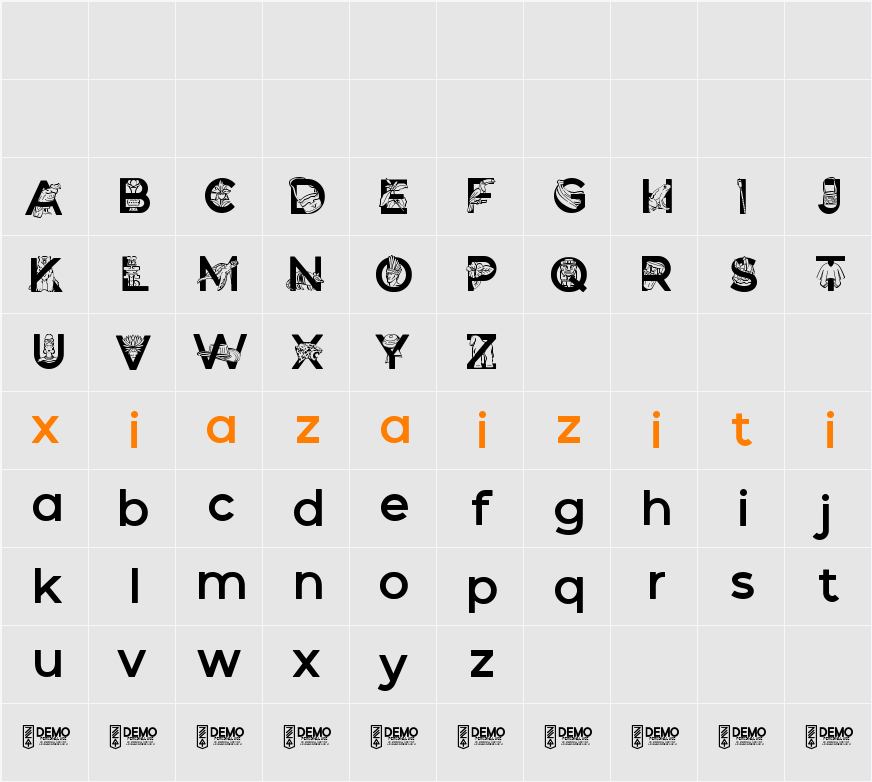
Zilap Colombia DEMO
Zilap Colombia DEMO,这款字体结构工整、笔画清晰,兼顾美观与易读性,适用于标题、正文、海报、包装、LOGO 等多种场景。字形优雅稳定,风格百搭耐看,适配日常排版与创意设计,让文字呈现更舒适、更具质感。Zilap Colombia DEMO一笔一画,皆是细节,以均衡的比例、流畅的线条打造舒适视觉体验,字形端正大气,风格简约现代。无论是商业设计、品牌宣传还是日常排版,都能轻松驾驭,让文字更有格调与力量。Zilap Colombia DEMO字体下载。